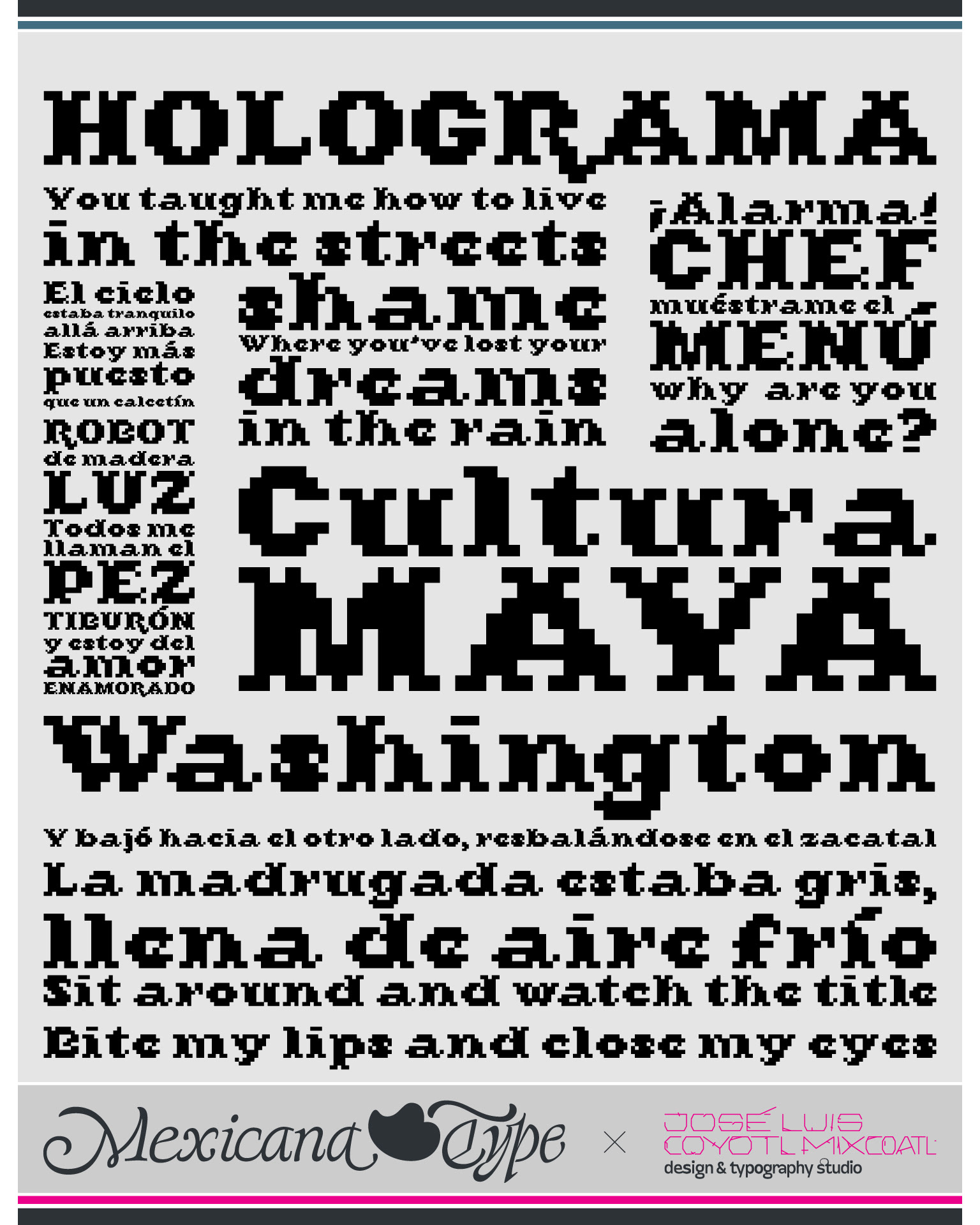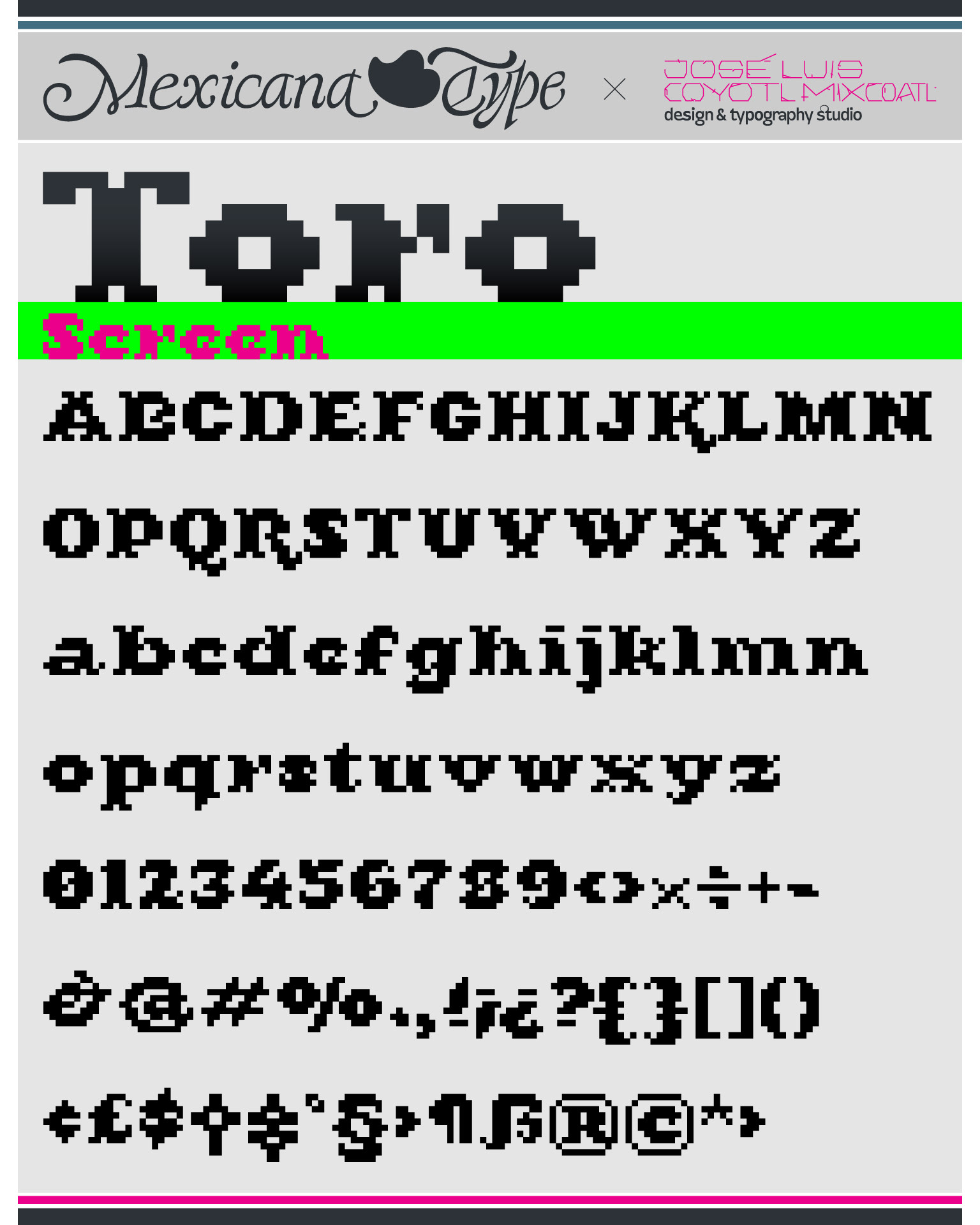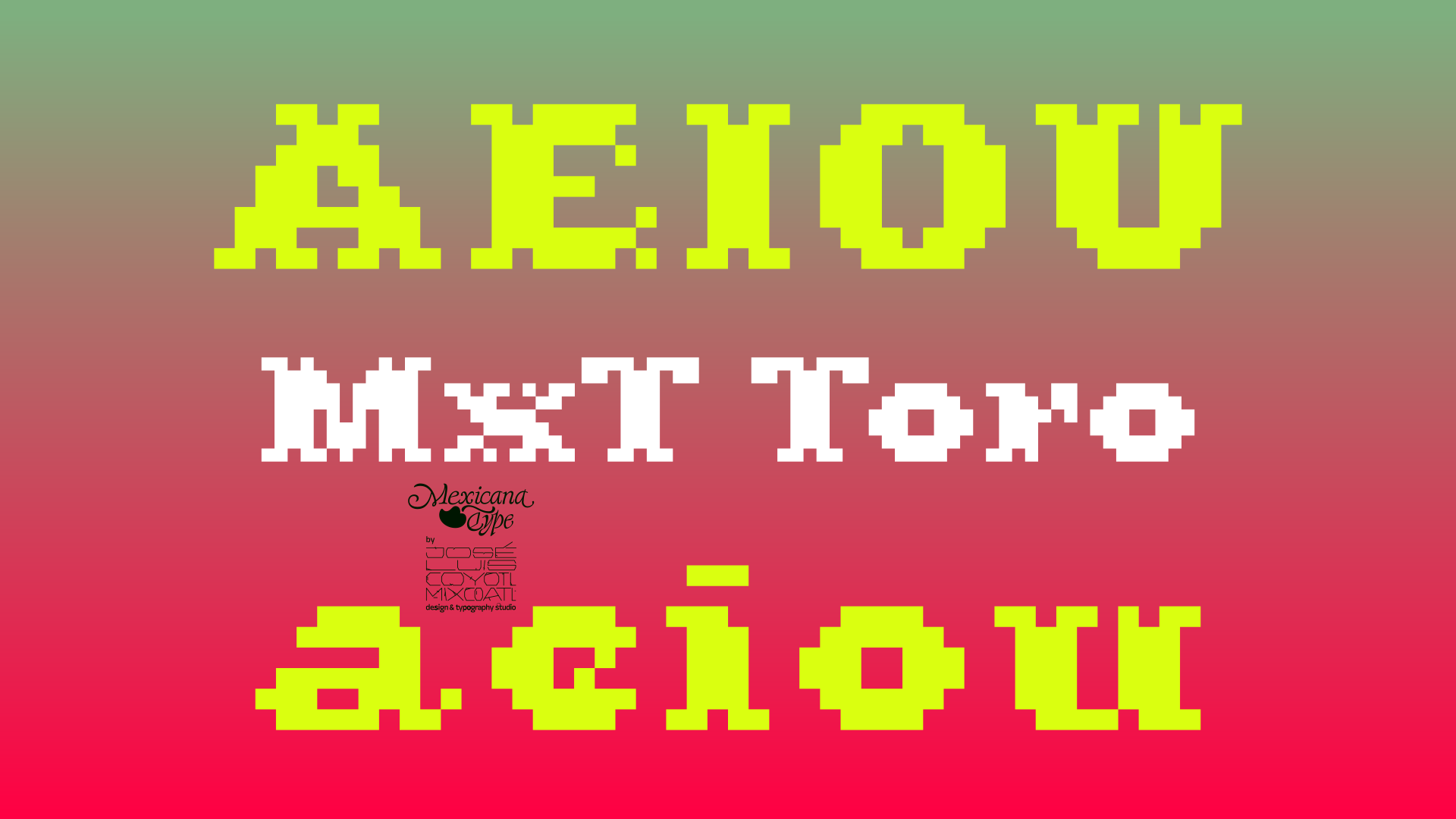
MxT Toro Diseñada originalmente para títulos de un proyecto editorial, eventuialmente se complementaron a un mapa de caracteres más amplio para hacerlo mas fácil de usar en otras aplicaciones en otros entornos gráficos. Inspirada por modulaciones de glifos y pirámides y escalinatas precolombinas principalmente.
Sus trazos simples, sólidos y abstractos, representan una mezcla interesante de elementos que para usos display, aunque funciona también en tamaños pequeños, pero su uso principal es para ser usado en títulos.